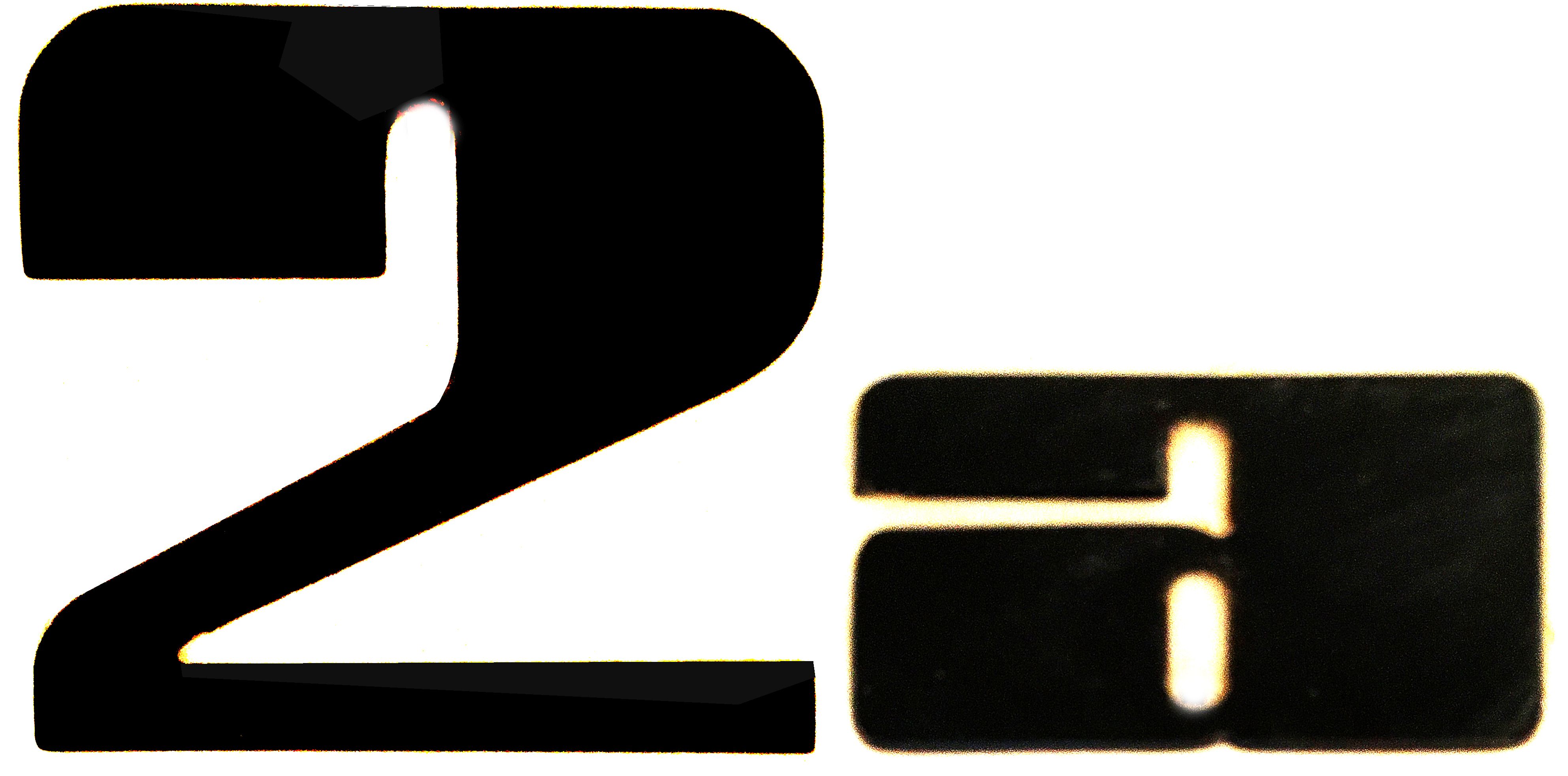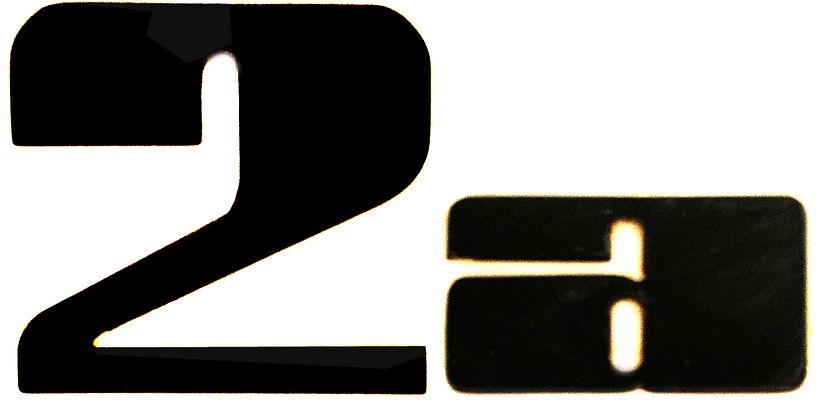
Identificar este tipo?
Solo tengo estos dos caracteres de la tipografía, que es muy de los 50s o incluso antes, las fotografié malamente con el móvil en una puerta antigua y las contrasté para intentar identificarlas en webs tipo "What Font Is" y ninguno de esos sitios me la identifica, de modo que si algún miembro sabe a fondo del tema igual me da una pista...
La más parecida que he podido encontrar es una fuente comercial de Canada Type:
Archie Pro